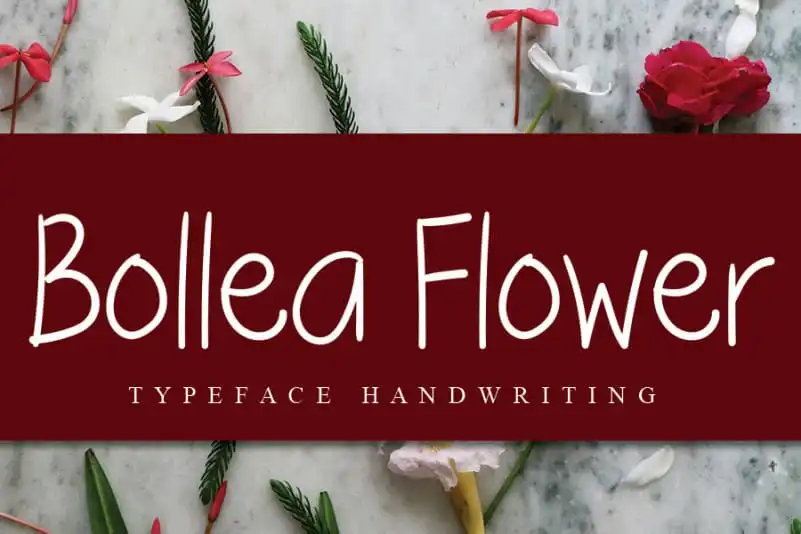
Bollea Flower Handwritten Font – Fonte Grátis
Bollea Flower Handwritten Font
A Bollea Flower Handwritten Font é uma elegante caligrafia que transmite facilidade e amabilidade. Suas características despojadas fazem com que a fonte pareça natural, fluida e extremamente versátil. Perfeita para uso em contextos variados, seja em fundo ocupado ou como um título de destaque sozinho. Suas linhas finas e traços delicados criam um contraste suave entre texturas distintas, tornando-a uma escolha ideal tanto para aplicativos profissionais quanto para designs pessoais. Esta fonte é perfeita para aqueles que buscam um toque artesanal em seus projetos digitais, oferecendo um caráter único e sofisticado a cada letra.